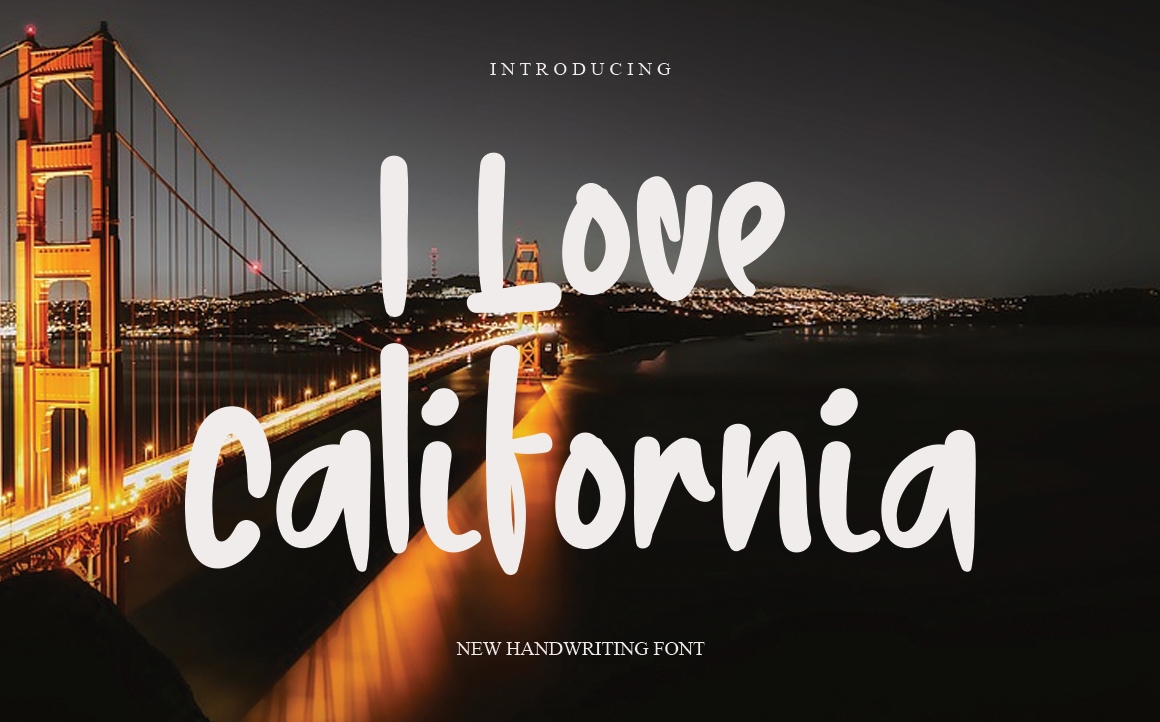
I Love California Font – Download Grátis
Esta é uma fonte cuidadosamente criada pela designer LevinCreative, com um estilo casual e encantador. Ela é perfeita tanto para aqueles que desejam uma fonte versátil e divertida para Instagram Stories quanto para quem busca um script gráfico elegante para projetos DIY. Com essa fonte à mão, qualquer ideia criativa transforma-se em uma verdadeira obra de arte! Se você está buscando uma fonte única e divertida, a LevinCreative ‘I Love California’ é o elemento perfeito para dar vida ao seu próximo projeto gráfico.